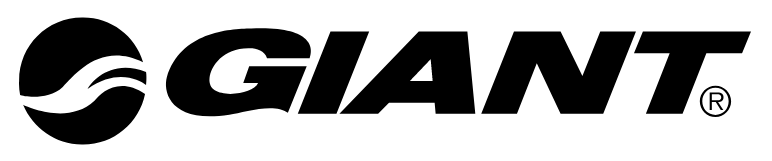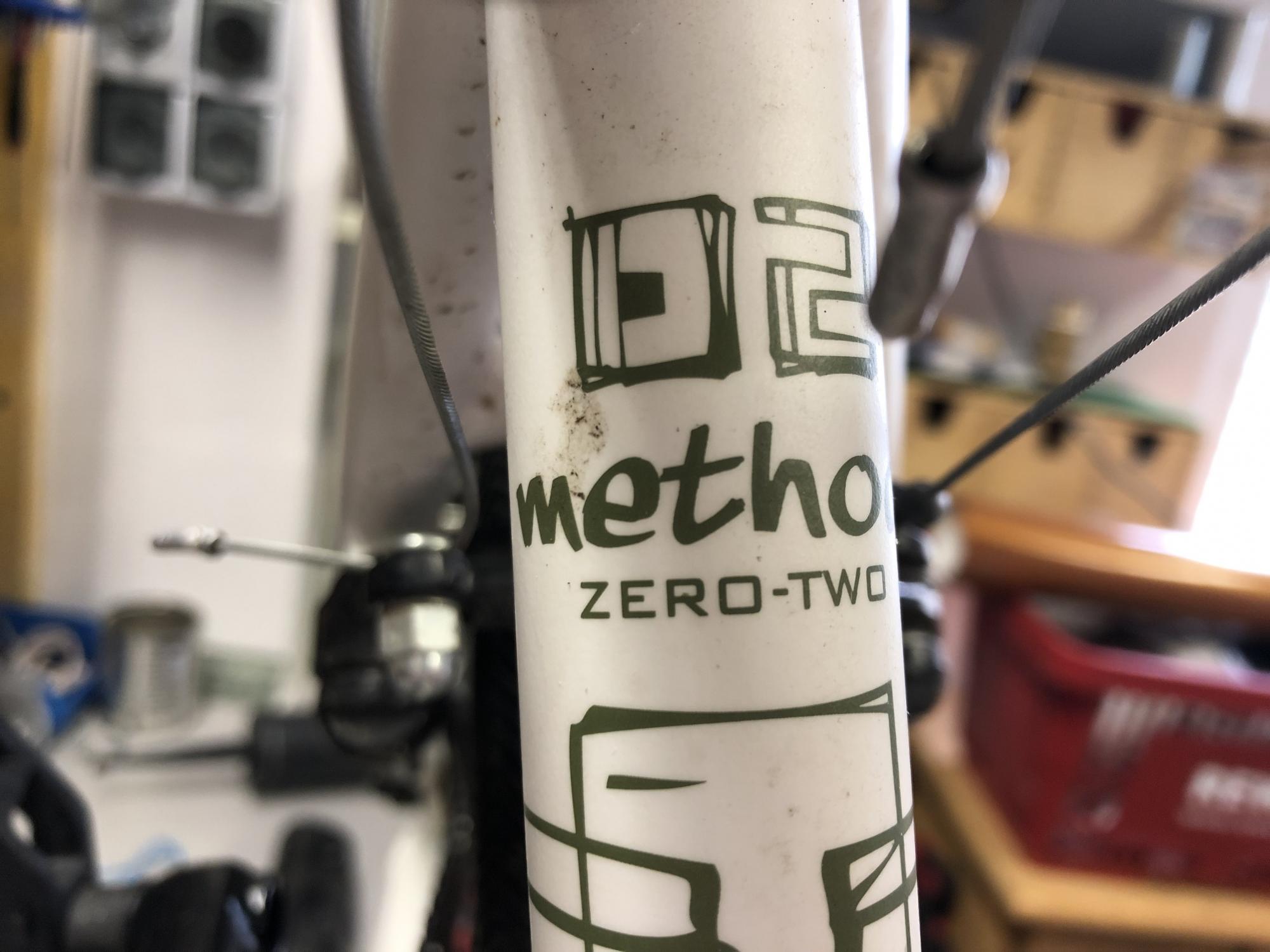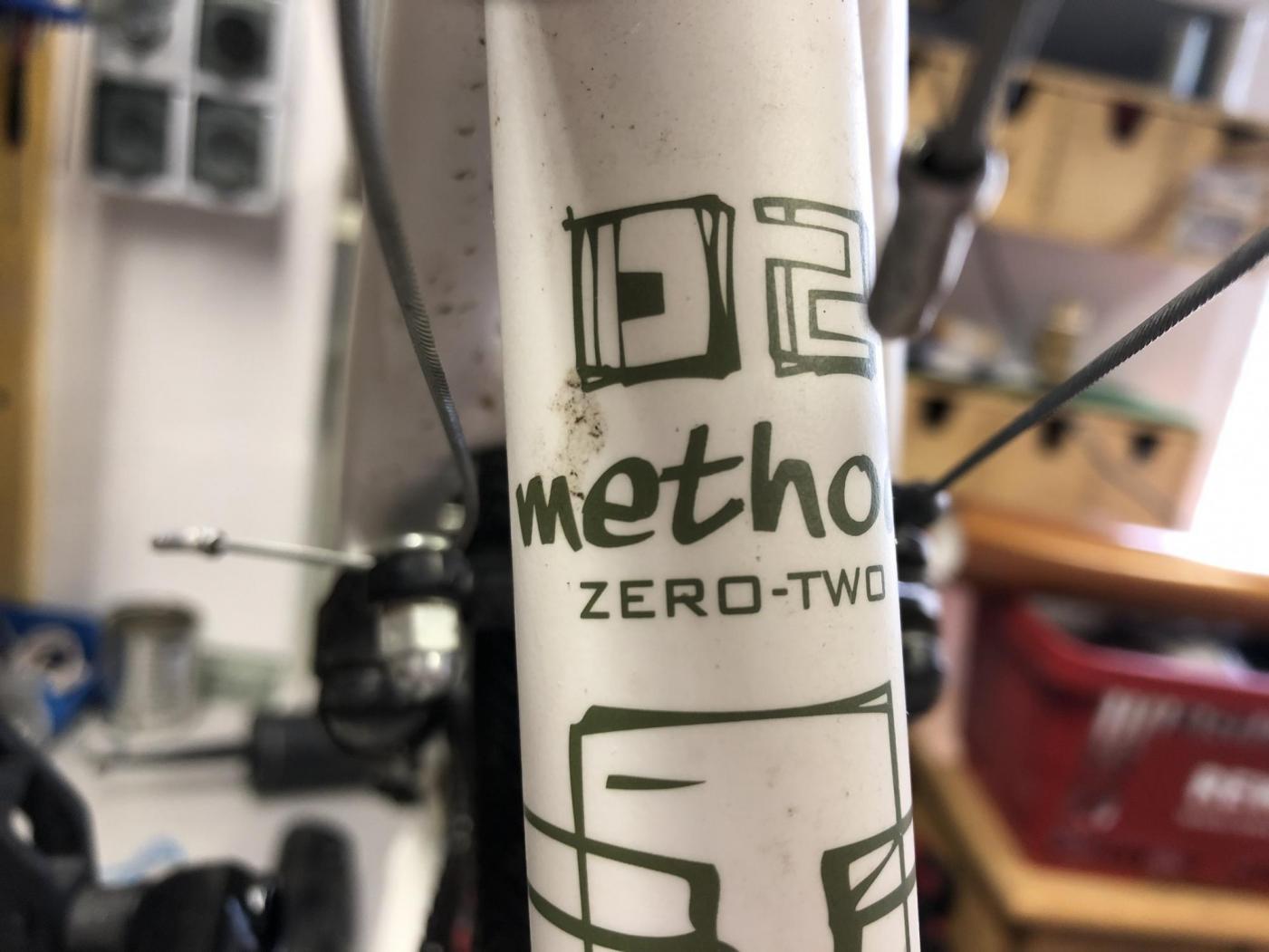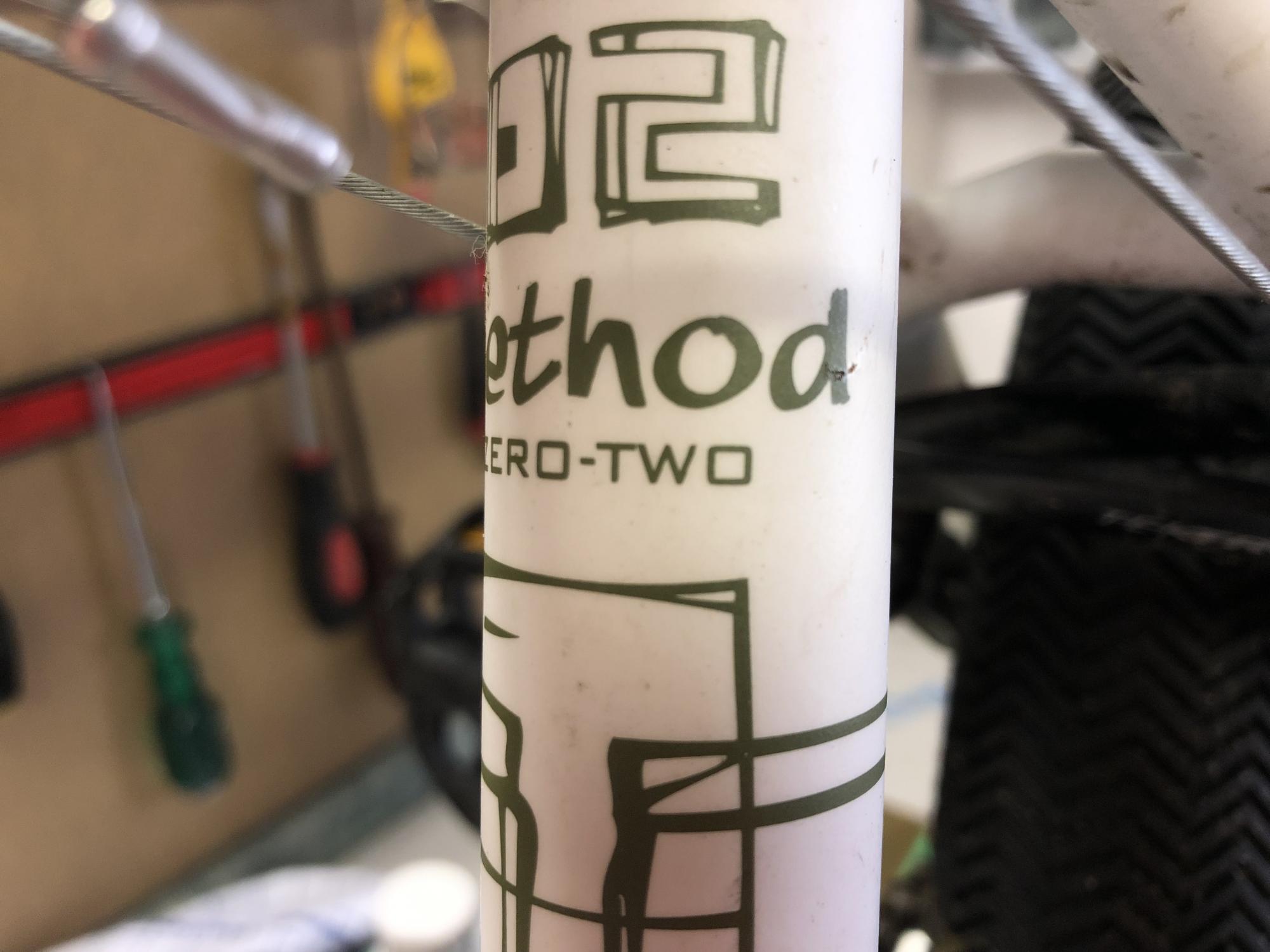
habe diese Schrift auf einem Bike gesehen (Giant)
hallo ich habe auf einem Fahrad eine Schrift gesehen und finde sie toll weis aber nicht welche es ist  mfg
Irgendwas gewöhnliches wie Helvetica. Verschieft, in die Breite gezerrt. Das G bearbeitet. Fertig ist das Logo.
Wenn es effizient sein soll: Helvetica Black Extendend Oblique nehmen, das G versaubeuteln und das A auf der Linken Seite etwas schmaler machen. Das sollte für das Erste ausreichen.
Hier habe ich noch eine schrift von dem Rad (dieses method) welche ich noch interesannter finde und sie leider nicht kenne, also bitte nochmal eure Hilfe
nochmal ich  ist das "02" über dem method auch eine schriftart? danke im voraus
Mir kommen diese Lettern irgendwie bekannt vor und ich glaube es könnte eine Schrift sein. Aber ich konnte diese in meinen Dokumenten und auf diversen Freefont-Seiten unter dem Tag „Square“ nicht finden. Ich habe aktuell keine Idee mehr wie ich erfolgversprechen auf die Suche gehen könnte.